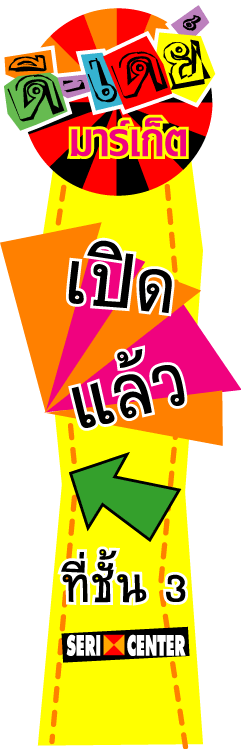
ต้องขอขอบคุณทุกท่านที่ให้ใช้ตัวหนังสือนะค่ะ สวยและน่ารักดีค่ะ อันนี้ออกแบบเป็นป้ายบอกทางค่ะ
ถ้ามีผลงานจะเอามาใหดูกันอีกนะค่ะ และขอให้กำลังใจทุกท่านในการออกแบบตัวหนังสือนี้ต่อไปนะค่ะ